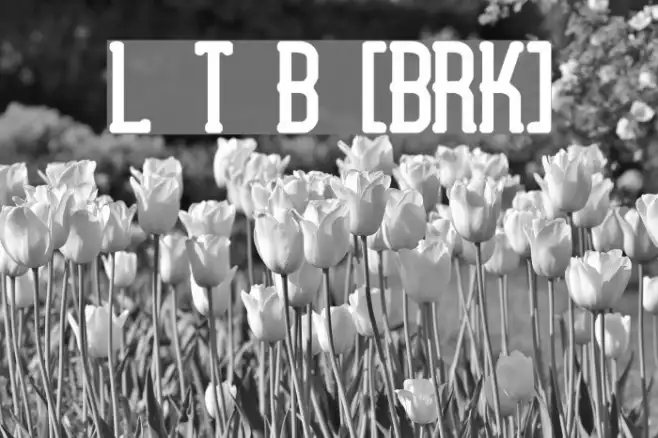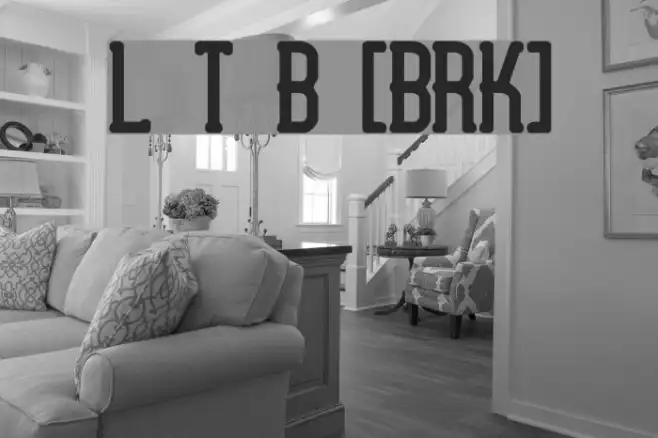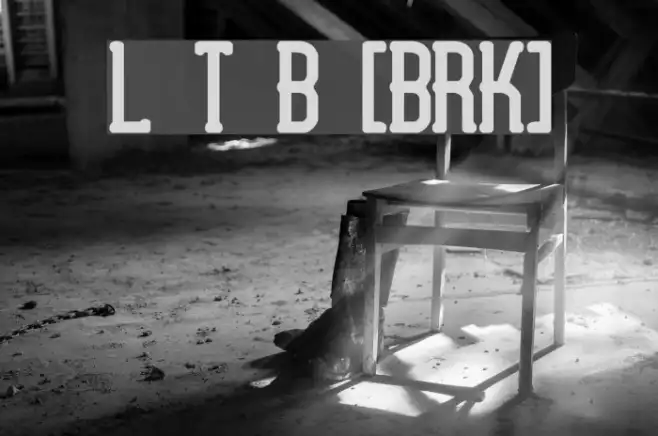
Lucid Type B [BRK] Font
| Gesamtstil | Playful, Modern |
| Vorgeschlagene Projekte | Ideal for children's books, playful branding, posters, and creative digital content. |